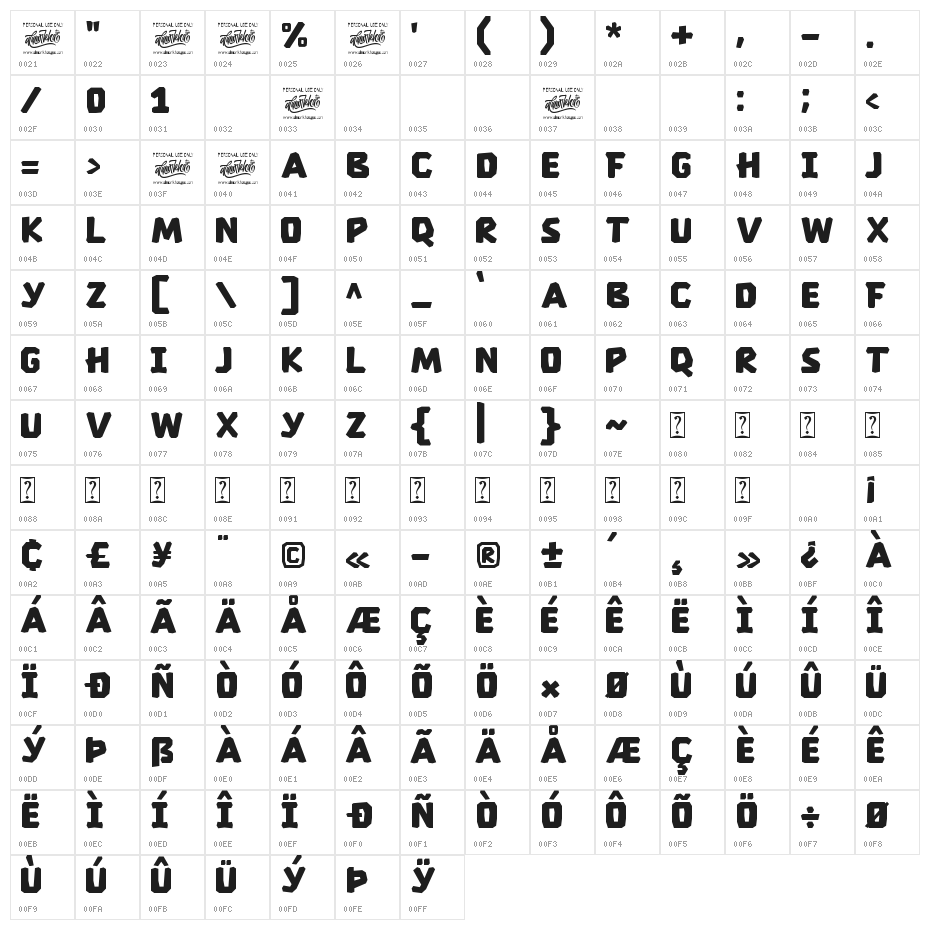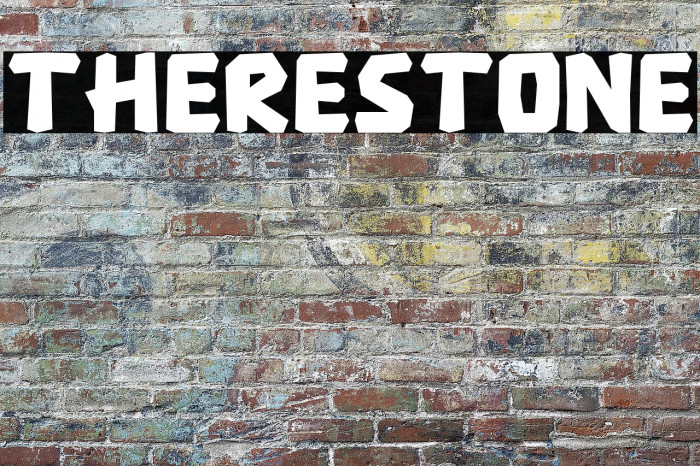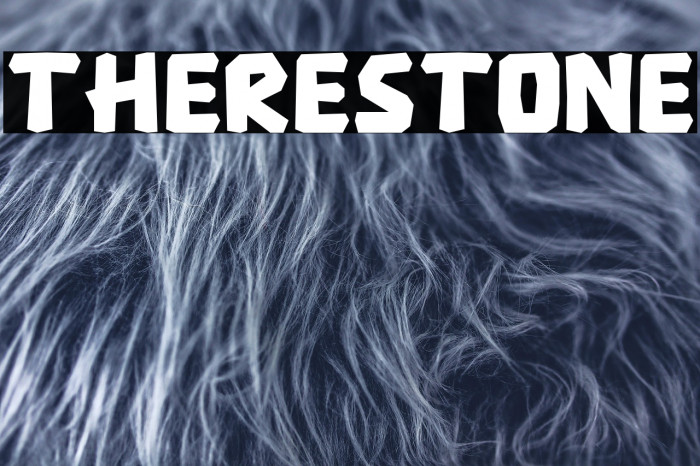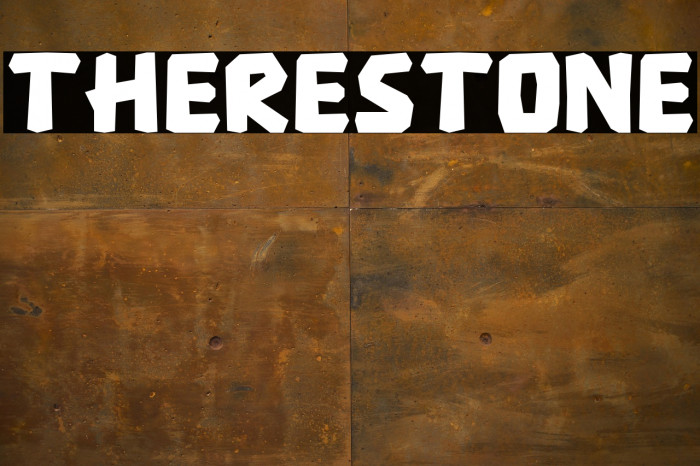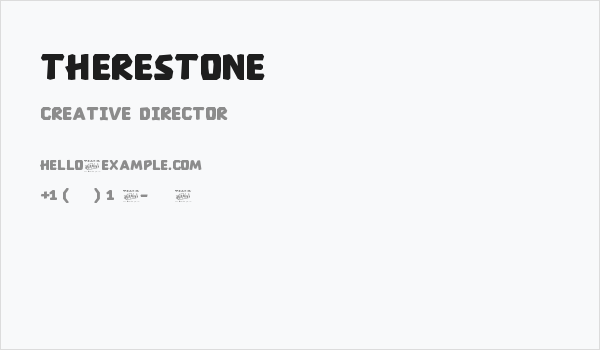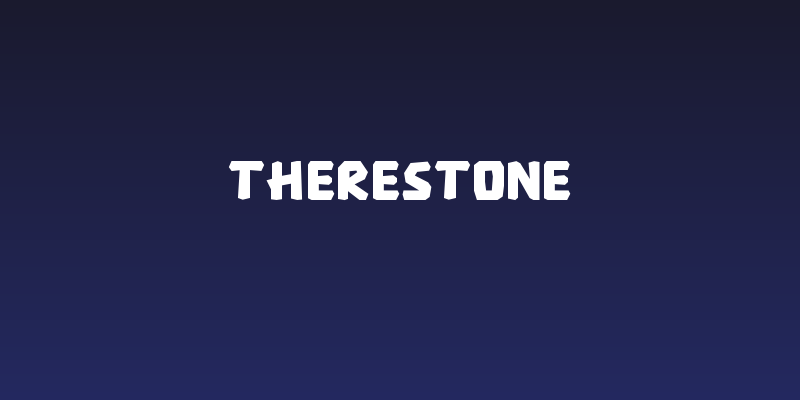
Therestone Font
| Stil general | Industrial, Rugged |
| Proiecte propuse | Ideal for posters, logos, branding, and signage that require a strong and bold statement. |